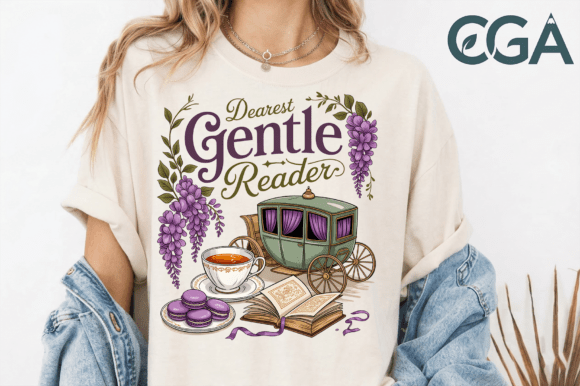
Dearest Gentle Reader PNG
Поиск подходящих элементов дизайна может быть сложным, но Dearest Gentle Reader PNG предлагает исключительную коллекцию, которая мгновенно улучшит вашу работу.
Созданный с высокой точностью, Dearest Gentle Reader PNG предоставляет чистые векторы, плавную типографику и коммерческую лицензию для вашего спокойствия.